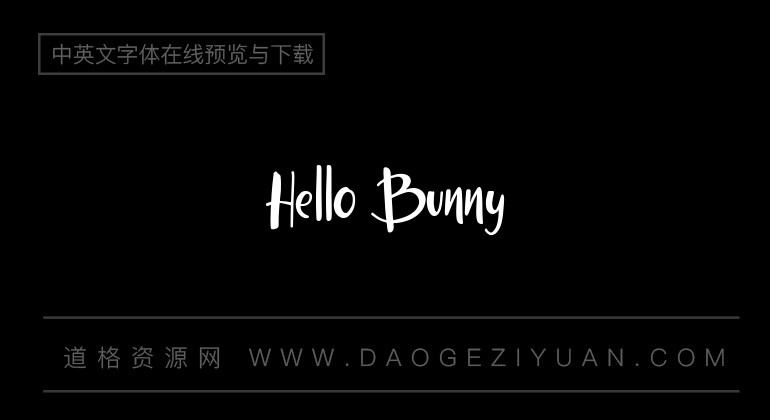
Hello Bunny
Hello Bunny是一款由Fontfabric创作的手写体字体,它采用简洁清新的风格,拥有清晰的线条,可以用于各种类型的设计作品,如海报、卡片、网页等。它的特点是细节精细、字符连贯,能够提供出色的视觉效果,使设计作品更加细腻、精致。
Hello Bunny是一款非常不错的手写艺术字体,具有很好的视觉感,适合于文化类的宣传设计、商业类品牌的广告和产品包装设计以及个性化文字排版等较多场景。